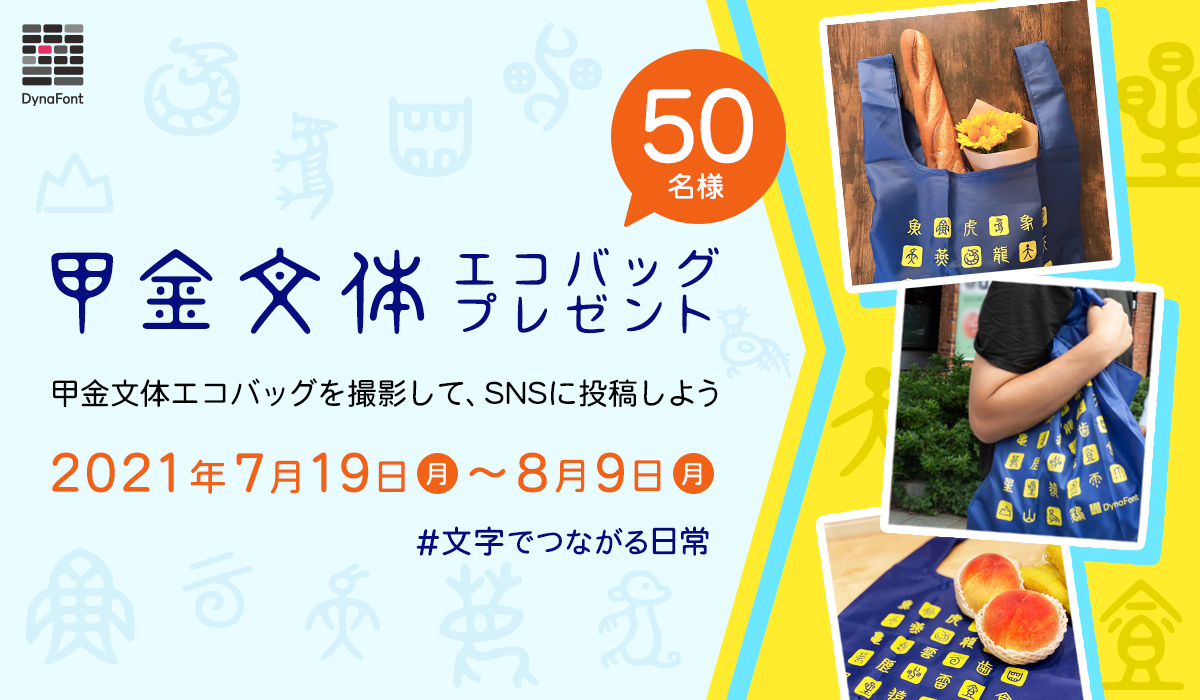
- ダイナフォントの「甲金文体」の エコバッグがもらえる「ダイナコムウェアSNS 2021 summerキャンペーン」が7月19日から開催中
ダイナフォントの「甲金文体」の エコバッグがもらえる「ダイナコムウェアSNS 2021 summerキャンペーン」が7月19日から開催中
ダイナコムウェアは、2021年7月19日から8月9日の期間中、ダイナコムウェアSNS 2021 summerキャンペーンとして、抽選で50名に「甲金文体」を使用してデザインした「甲金文体エコバッグ」をプレゼントすることを発表した。
過去と現代をつなげる文字「甲金文体」
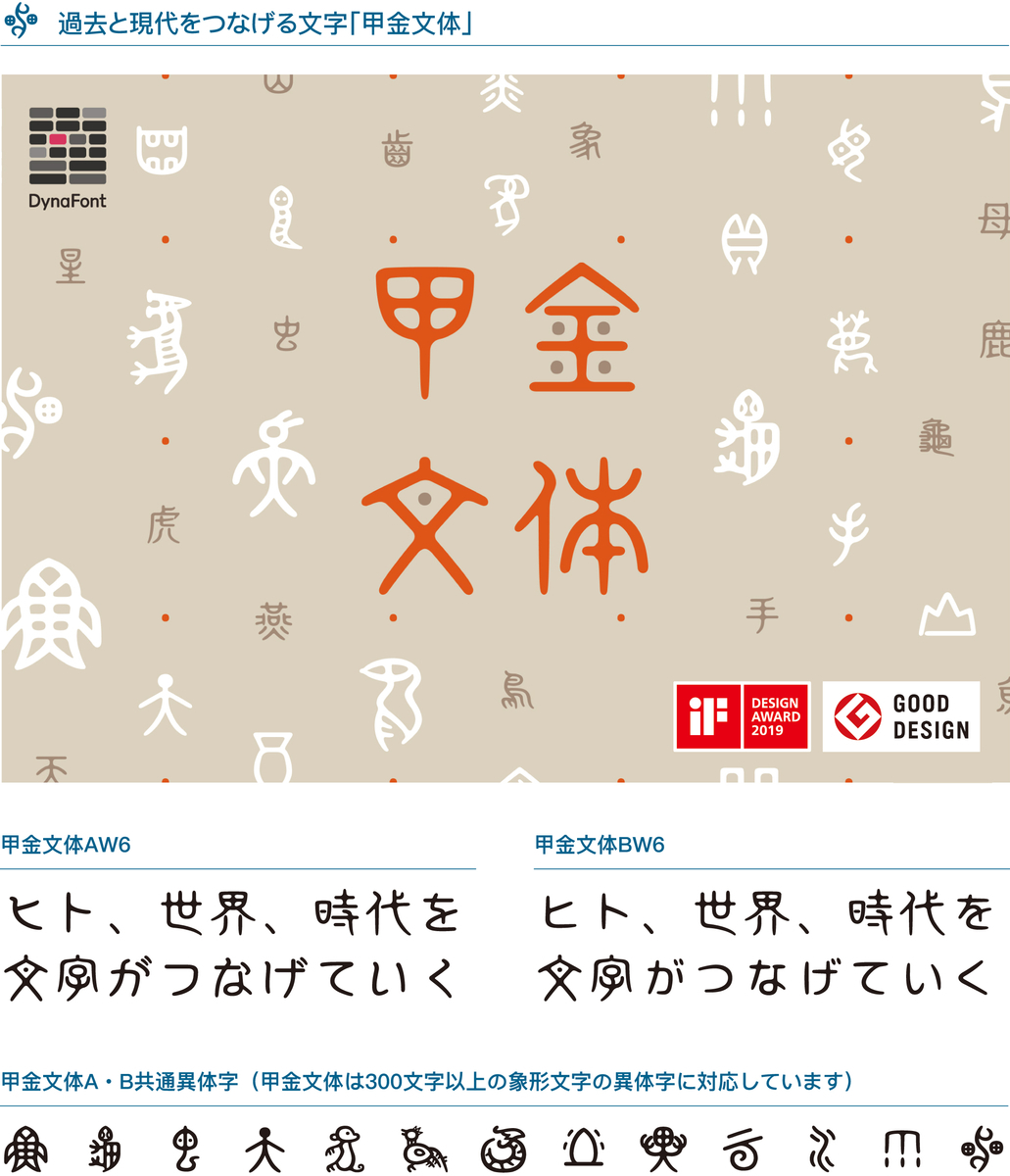
「甲金文体」は、古代文字の美しさに着目して甲骨文や金文体の特徴である幾何学的な模様を取り入れた素朴ながらも気品さも備えた書体。
「グッドデザイン賞」や「iFデザイン賞(iF Design Award)」を受賞している。
文字で日常を彩る「甲金文体エコバッグ」
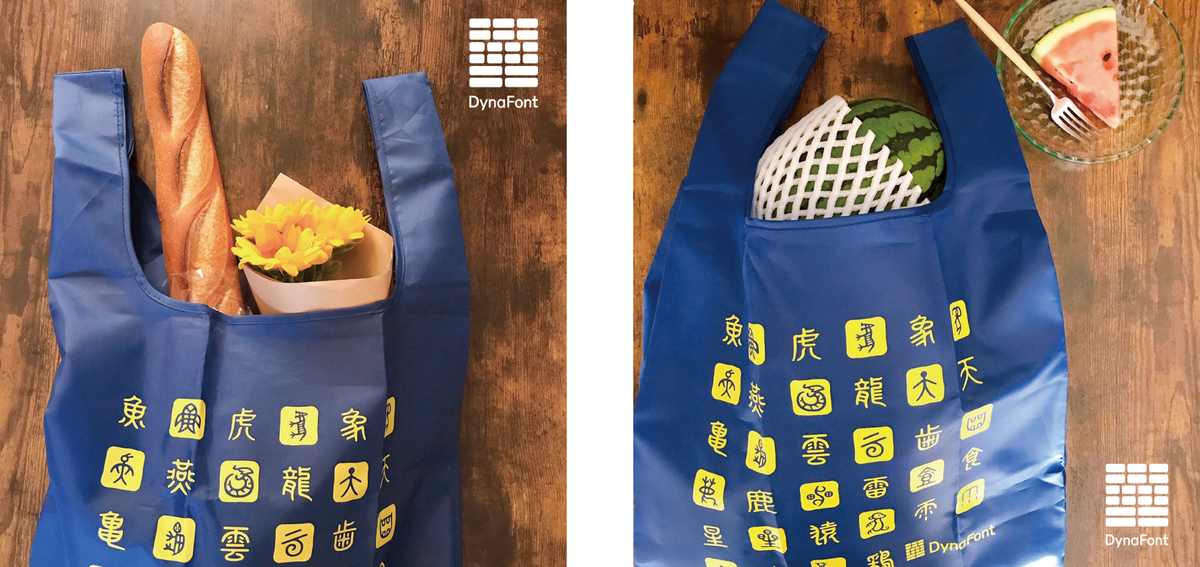
「甲金文体」を使用した文字に、ブルー・イエローという爽やかなカラーで彩りを加えたデザインになっている。
また、丈夫な素材で大き目サイズながらも簡単に折りたためお出かけにも買い物にも便利で環境にも配慮している。